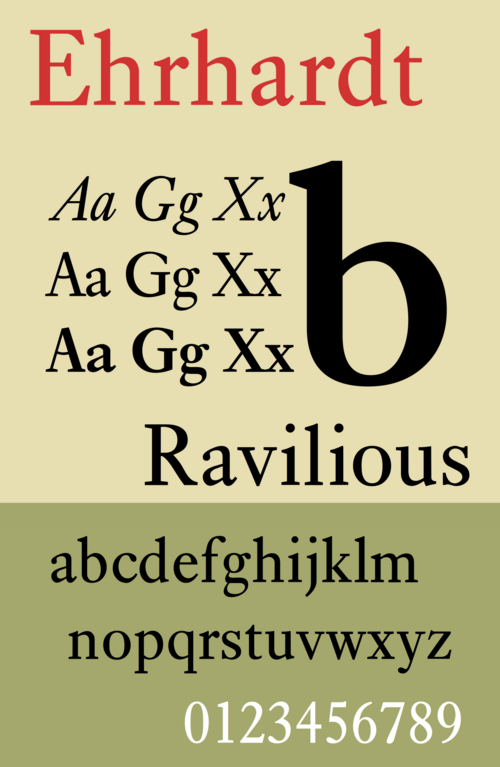
| カテゴリ | セリフ |
| 分類 | 旧 オランダ語 |
| デザイナー | ニコラス・キス |
| 鋳造所 | モノタイプコーポレーション |
| リリース日 | 1938年、1680年代 |
| デザインは | ジャンソン |
| バリエーション | 艦隊のタイトル |
エアハルトは、モノタイプ社の英国支社が1938年に発表した古いスタイルの セリフ書体である。エアハルトは、ライプツィヒのエアハルト鋳造所で販売されていたオランダのバロック様式の「頑丈なオランダ文字」の印刷用活字を現代風にアレンジしたものである。[1]これらは、1680年から1689年にかけてアムステルダムに滞在していたハンガリー系トランシルヴァニア人の牧師兼パンチカッターのミクローシュ(ニコラス)トートファルシ・キスによって切り出された。 [2] [3]
1937 年から 1938 年にかけて、モノタイプ社は現代の使用法に合わせてこの書体を再カットし、書籍用の人気書体となりました。Ehrhardt はやや凝縮されたデザインで、垂直感が強く、くっきりとした外観になっています。
歴史的背景
トランシルヴァニアの プロテスタント牧師で教師のミクローシュ・キスは、ハンガリー語のプロテスタント訳聖書の印刷を手伝うためにアムステルダムに派遣された後、印刷に深い関心を持つようになった。[4] [5]この時代はネーデルラントにとってかなりの繁栄期であり、ネーデルラントの印刷様式がヨーロッパ中に大きな影響力を持ち、ネーデルラントが新しい書体の作成の中心地となっていた。[6] [7] [8]彼は、印刷業者や政府からの委託を受けて、金属活字の鋳型を作る親方として使用されるパンチカッター、つまりパンチの彫刻師として第二の職業に就いた。キスは1689年頃にトランシルヴァニアに戻り、帰国の途中、ライプツィヒに母型(活字を鋳造するために使用する鋳型)を残していった可能性がある。[9] [a]ライプツィヒのエールハルト活字鋳造所は、1720年頃にそれらの現存する見本シートを公開した。[10] [11]
キスの書体は、前世紀に発展したオランダとドイツの印刷術の伝統を受け継いでおり、後に「オランダ風」( goût hollandois )と呼ばれるようになった。この用語は、次の世紀のピエール・シモン・フルニエの著作に由来する。 [12]これにより、クロード・ガラモンドが彫刻した滑らかで均一な構造の書体や、水平なクロスストロークの「e」など、フランスの活字鋳造法の影響が生まれ、ストローク幅を広げ、xハイト(小文字の高さ)を上げ、ディセンダーの長さを短くすることで、ページ上で著しく暗い色を実現した。 [13]
キスの現存する母型は、最初はステンペル社が入手し、現在はダルムシュタットの印刷博物館のコレクションに収められている。[14]これらは、かつてはライプツィヒを拠点に活動していたオランダの印刷業者アントン・ヤンソンが作成したと考えられていたため、ヤンソン・デザインと呼ばれることが多かった。それに応じて、ライノタイプ社が同じデザインをより簡略化した形で復活させたものもヤンソンと名付けられた。[15] [16]キスが書体の製作者であることが再発見されたのは、彼の名前が特定されたハンガリーのアーカイブ資料(自伝を含む)の書体と比較したためである。[17] [18] [19]
近代史
モノタイプ社による Ehrhardt の開発は、タイムズ ニュー ローマンの開発に成功した直後、印刷史研究家のスタンレー モリソンの経営下で進められた。[20]これは、ドイツのステンペル社が所有していた現存するオリジナルの母型から手組された活字を使用してヤンソンの書体で本を印刷できたダニエル バークレー アップダイクなどのアーツ アンド クラフツ時代の優れた印刷業者がヤンソンの書体のデザインを高く評価していたことを認識したことから始まった。モリソンは、1920 年代以降、アップダイクと広範囲にわたる書簡の中で、ヤンソンの書体の歴史について知っていることを話し合っていた。[21]ヤンソンの書体のホット メタル印刷用の現代版は、ライノタイプ社とモノタイプのアメリカ支社によって同時に作成されていた。[9] [22]さらに、モリソンはドイツの書籍取引の中心地であったライプツィヒの印刷の歴史に興味を持ち、後にそのテーマに関する記事を執筆している。[18]
エアハルトの開発は、過去 50 年間に金属活字の使用をやめることなく起こった印刷技術の一連の進歩を受けて行われた。パンタグラフ彫刻により、大きな図面から正確にパンチを機械加工できるようになった。これにより、希望する文字の正確なサイズで鋼から手作業でマスターパンチを彫り出した歴史的な書体よりもきれいな結果が得られた。また、同じ一貫した文字スタイルで幅広いサイズの文字を迅速に開発することも可能になった。ただし、実際には、文字や間隔を広げたり、x 高さを大きくしたりして、異なるサイズで鮮明な画像を生成するようにデザインを調整した。[24] [23]さらに、当時のホット メタル タイプセッティングシステムによって手作業による印刷は廃止され、その中でモノタイプのシステムは最も人気のあるものの 1 つであった (ライノタイプのシステムと競合していた)。どちらも、キーボードの制御下で金属活字を素早く鋳造できるため、手動で金属活字を鋳造して印刷機に差し込む必要がなくなった。活字を在庫する必要はなく、活字を鋳造するための型として使われる母型だけあればよいため、印刷業者はより幅広いフォントを使用できるようになり、多様な書体に対する需要が高まった。一方、芸術面では、18世紀と19世紀に導入された機械的で幾何学的なディドン書体の使用が好まれるようになったが、それ以前に開発された「古いスタイル」のセリフ書体への関心が復活し、この変化は永続的なものとなった。[25] [26] [27]同時に、ホットメタルタイプセッティングは新たな制限を課した。モノタイプのシステムでは(リノタイプのシステムほど制限はなかったが)、1行に収まる文字数を機械的に数えるために、文字の幅は一定に制限され、それにもかかわらず調和のとれた文字を作成するために注意が必要だった。[27]
モノタイプ社は、再発見された見本シートをソースとしてEhrhardt書体の復活版を開発し、同時に、少し前のオランダのバロックパンチカッターであるChristoffel van Dijck(1669年没)の作品の復活であるVan Dijckにも取り組んでいました。[28] [29]モノタイプのベテランデザイナーRobin Nicholasによると、Ehrhardtの元の作業タイトルは「Old Holländische」でした。[30]
フリッツ・ステルツァー率いるサリー州サルフォーズのモノタイプ製図室チームによって開発されたこのプロジェクトは、純粋に忠実な復刻版から、より密度が高く凝縮されたデザインへと方向転換した。 [31] [32] [33]これによって、市場に出回っている他のヤンソン復刻版とは一線を画した。[9] [34] [35]ニコラスは「これはモリソン流のヤンソンの解釈だと思う。読みやすさと経済性を高めるために、少し太く細くした」とコメントした。[30]植字の専門家ヤニス・ハラランボウスは、モノタイプのマネージャーから、この書体は特にドイツでの販売向けに「フラクトゥール(1930年代のドイツではまだ非常に人気があったブラックレターまたは「ゴシック」書体)に弱い人にアピールするために」デザインされたと聞かされたと書いている。[36]緻密なデザインはブラックレターとよくマッチする可能性があり、ライプツィヒ印刷に関する記事の中でモリソンはこれがオリジナルのデザインスタイルの背後にある動機だったのではないかと示唆している。[18]エアハルトの技術的な生産は、当時のモノタイプの標準的な方法に従った。文字は、モノタイプがドイツの印刷業界から採用したステルツァーが率い、訓練した経験豊富な製図室チームによって、大きな計画図で紙に描かれた。デザインを実行した製図スタッフは女性が多く、多くの場合、地元や近くのライゲート美術学校から採用された。これらの図面から蝋写しが作られ、蝋写しはデザインの鉛版を作成するために使用された。これらの版は、ベントンパンタグラフで母型を刻印するための金属パンチを機械加工するための設計図として使用された。[37] [38]当時のモノタイプ社の標準的なやり方は、まず限られた数の文字を彫刻し、それをもとに試し刷りを印刷してページ全体の色のバランスをテストしてから、残りの文字を完成させることだった。
完成したデザインは、1938年にモノタイプ社の雑誌『モノタイプ・レコーダー』に、署名のない宣伝文とともに初めて掲載された。カーターはこれを後に「モリソンのアクセント」と呼んだ。 [9] [39]後に、ライプツィヒの印刷の歴史に関するモリソンの記事がそこに植字され、モリソンの死後には彼の作品の記念論文集にも使用された。 [18] [40]
特徴的な機能
エアハルトの特徴は、緩やかにカーブしたバーが「B」の中央のリンクと一致する「A」、両側に広がったセリフを持つ幅広の「T」、左側に足のない「b」などである。イタリック体では、「J」には横棒があり、「w」は上と左に向かって鋭く逆カーブし、「v」は左側に装飾がある。 [1] [41]この書体は、ほとんどの旧式セリフ体フォントの基準からすると、ストロークのコントラスト(太いストロークと細いストロークの差)が高い。コンパクトな行間を可能にするために、ディセンダーは適度に短く保たれている。[42]
受付
エアハルトは発売当初からかなりの注目を集め、モノタイプの宣伝資料では「一部の専門家の意見では、タイムズ・ニュー・ローマン以来最も重要な新しい書体」と宣伝された。[43]しかし、エアハルトは、タイムズ、ペルペチュア、ガラモンド、ベンボなど、戦間期のモノタイプの他の古典的なセリフ体のデザインの多くに比べると、あまり知られていない。[31] [b]
ハリー・カーター(ジョージ・バデイとともにキスの現代版と位置づけた)は「モノタイプ・エアハルトの文字はジャンソンの文字に似ているが、その文字を載せたページの見た目は異なる。ジャンソンはより丸みを帯びており、太字と細字のコントラストが大きい」と書いている。[9] 1970年代の著作で、カーターはコンデンシングについて懸念を抱いており、キスの作品を「正確な単調な作業」に変えそうになったが「成功した書体だ」と述べている。[9]また、キスが作成し、フィレンツェのドゥカーレ印刷所に販売されたコンデンシング書体の方が、より本物のモデルになったかもしれないと示唆している。[9] [2]印刷史家ジェームズ・モズレーはモリソンの回想録『A Tally of Types』の書評で、オリジナルの金属活字はモノタイプの初期のデザインに比べて「粗雑に描かれている」と評し、これはモノタイプの工場の経営が主任技術者のフランク・ヒンマン・ピアポントの退職によって変更されたためだと示唆した。[45]
エアハルトを舞台にした著名な書籍には、オックスフォード・ワールドズ・クラシックス・シリーズ、新英語聖書、ペリカン・シェイクスピア、ペンギン60s、ヒュー・ウィリアムソンの教科書Methods of Book Designなどがある。[42] [46] [47] [48] [49]また、フェイバー&フェイバーやアイコニック誌でも使用されている。[50] [48]非常に珍しいこの書体の幼少期の変種も存在し、ジョン・バーニンガムのHey! Get off Our Trainのアメリカ版で見ることができる。[51]
拡張機能
モノタイプ社は後に、オリジナル版のローマン体とイタリック体に合うように、ボールド体とボールドイタリック体(一部のデジタル化ではセミボールドと呼ばれる)を作成した。 [9] [52](キスの時代には、真のボールド体は存在しなかった。[53])1967年にリリースされたFleet Titlingは、タイトル用の補助として意図された大文字のみのアルファベットだった。モノタイプ社と時折協力していた、ケンブリッジ大学出版局のデザイナーで、民間の印刷業者としても働いていたジョン・ピーターズによって作成された。[54] [55] [56]モノタイプ社はそれを自社のロゴとレターヘッドに使用した。[30] [57]さらに奇妙なことに、モノタイプ社は1960年代に、EhrhardtをInitial Teaching Alphabetの印刷のベースとして使用した。このアルファベットシステムは、子供に読み方を教えることを目的としており、tとcをテキストのベースラインより下に下げるなど、同じ文字で綴られる異なる音に代替文字を使用した。[58] [59]
デジタル化と代替バージョン
Monotype社はEhrhardtをTrueTypeおよびOpenTypeフォント形式でデジタル化した。Ehrhardtは標準版とプロフェッショナル版で販売されており、一部の版には数字やスモールキャップ(ローマン体のみ)が含まれている。コンピュータ出版の初期にデジタル化された他のいくつかのMonotype書体と同様に、EhrhardtはMonotype社とAdobe社の両方の名義で2つのリリースで販売されており、 Adobe社ではスモールキャップのない標準版のみとなっている。[1] [60] Fleet TitlingおよびInitial Teaching Alphabet版はデジタル化されていない。